Di postingan ini, Computer 1001 menyajikan 6 situs untuk download gratis ribuan font dekoratif / font display yang keren untuk digunakan di desain Anda.
Download Font Dekoratif di Dafont
Sudah banyak yang mengenal Dafont sebagai situs yang menyediakan banyak font keren yang gratis.
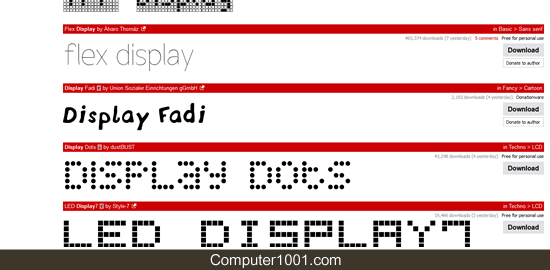
Download Font Dekoratif di Font Squirrel Display
Font Squirrel memiliki banyak koleksi font display.
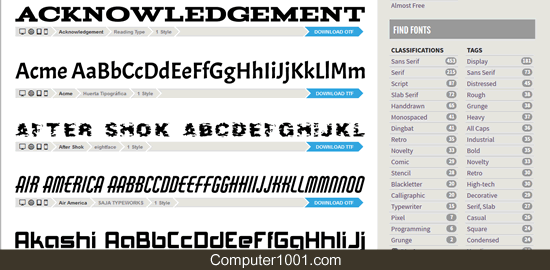
Download Font Dekoratif di Font Space – Display
Para desainer font profesional juga sering upload hasil desain mereka di Font Space.
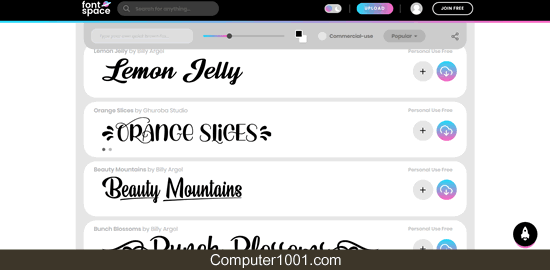
Download Font Dekoratif di 1001 Fonts – Display
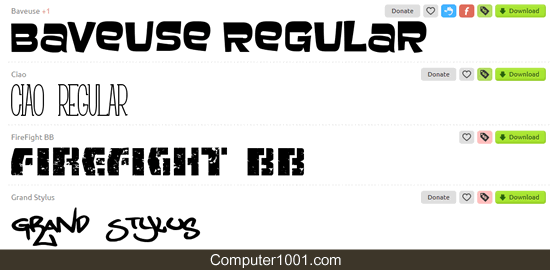
Download Font Dekoratif di Google Font – Display
Google Font memiliki berbagai variasi font display yang jumlahnya terus bertambah.
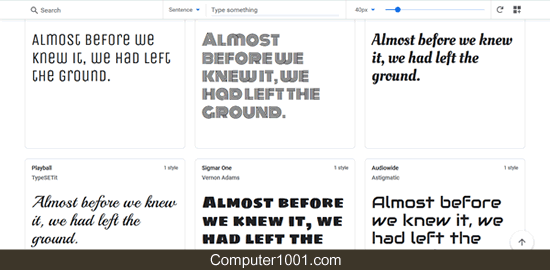
FDR Font Display
Di situs ini kita bisa unduh dan melihat contoh-contoh tampilan font pada berbagai desain banner yang keren.
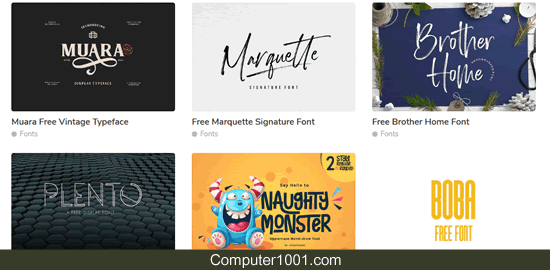
Sekilas Tentang Font Dekoratif (Font Display)
Font display atau font dekoratif adalah font yang digunakan untuk format teks yang singkat dan seringkali dalam ukuran besar (di atas 14 pt).
Contoh penggunaannya seperti di billboard, spanduk, poster, logo, kaos, kemasan produk, serta heading di majalah, koran, newsletter, website atau blog, sampul buku, catatan aesthetic, dan sebagainya.
Font display bisa berupa font serif, slab serif, didone, script, dan sans serif.
Ada juga font yang khusus dirancang untuk sebagai font display saja, dengan berbagai fitur dekoratif, ornamen, atau efek seperti shadow dan sapuan kuas; yang tampilannya unik dan eksentrik.
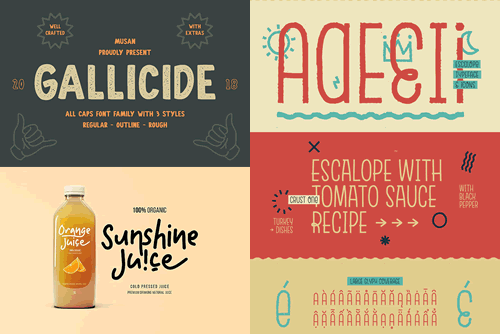
Kadang kita perlu berhenti sejenak dan memperhatikan dengan seksama tulisannya karena bentuknya yang tidak beraturan dan agak sulit dibaca.
Namun memang ini tujuan font display, yaitu untuk menonjolkan sesuatu, menarik perhatian, menciptakan dan membangun mood / perasaan (ringan, santai, serius, atau dramatis).